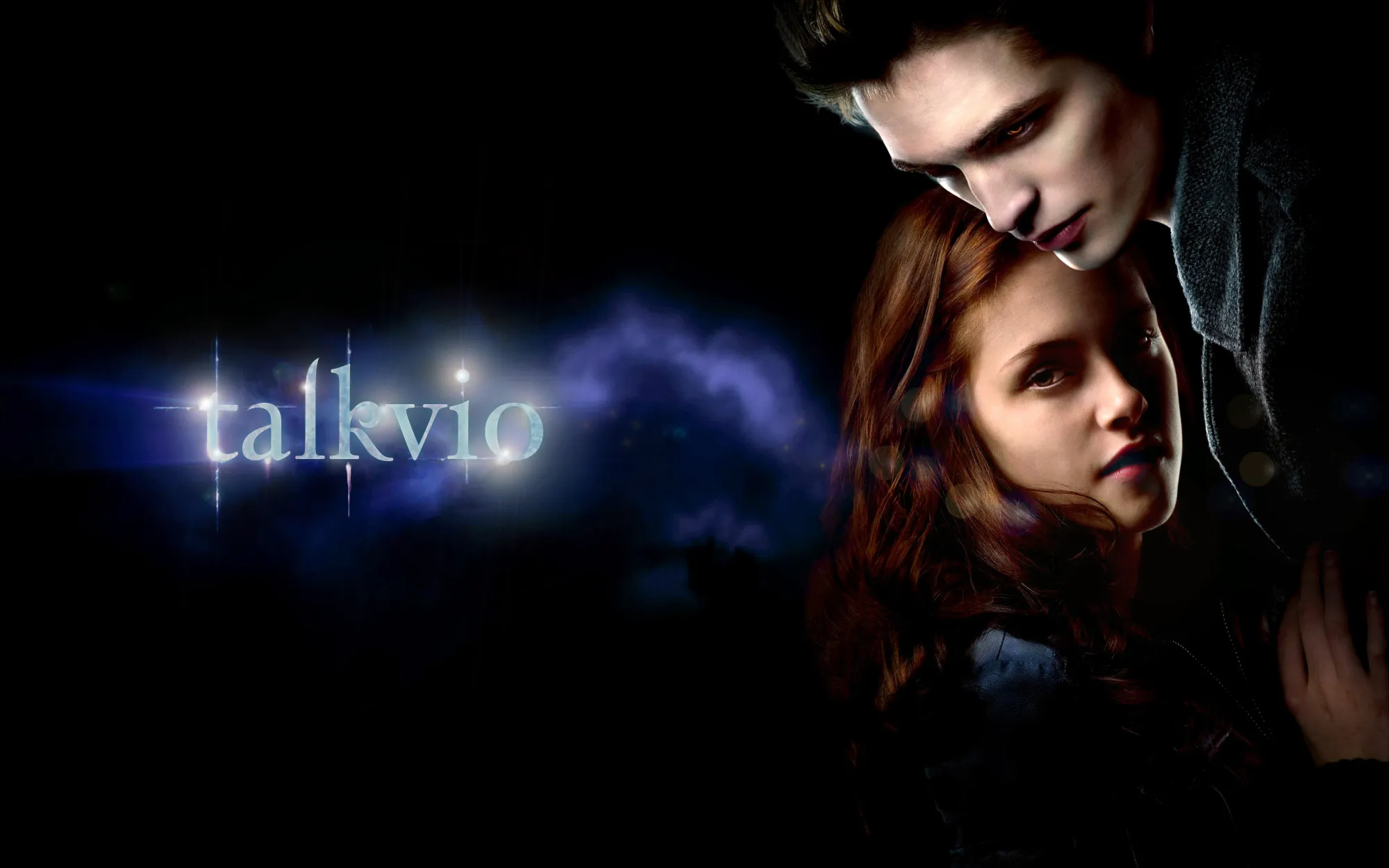
Назойливые мемы под саундтрек «Сумерек» сподвигли меня сделать шрифт этой картины.
Для названия каждого фильма франшизы был использован модифицированный шрифт Zephyr. Дизайнеры утончили некоторые линии, кое-где добавили более прямые срезы, ну и ещё сильнее скрутили завиток у буквы «g».
(Для постера выше был использован оригинальный Zephyr)
Для названия каждого фильма франшизы был использован модифицированный шрифт Zephyr. Дизайнеры утончили некоторые линии, кое-где добавили более прямые срезы, ну и ещё сильнее скрутили завиток у буквы «g».
(Для постера выше был использован оригинальный Zephyr)